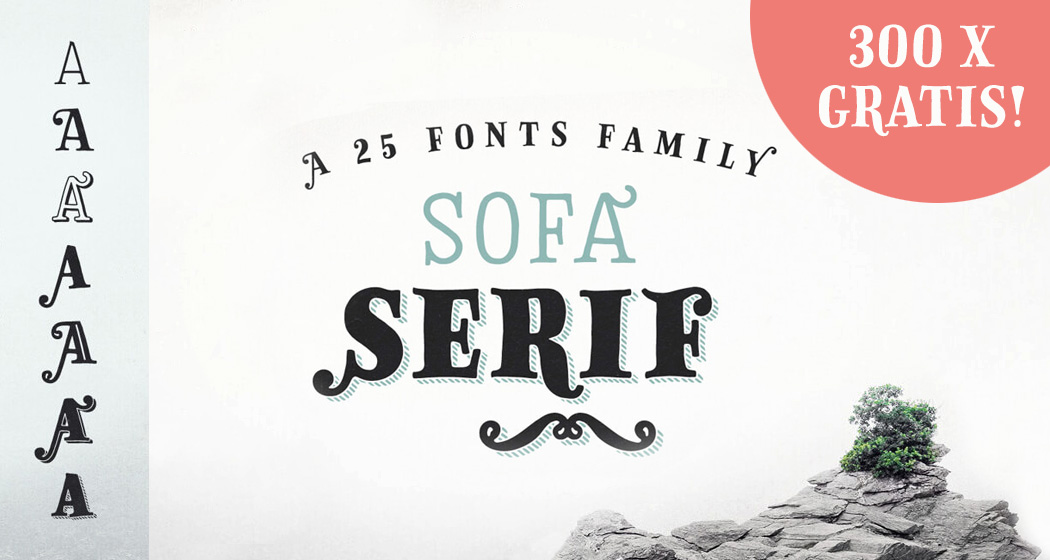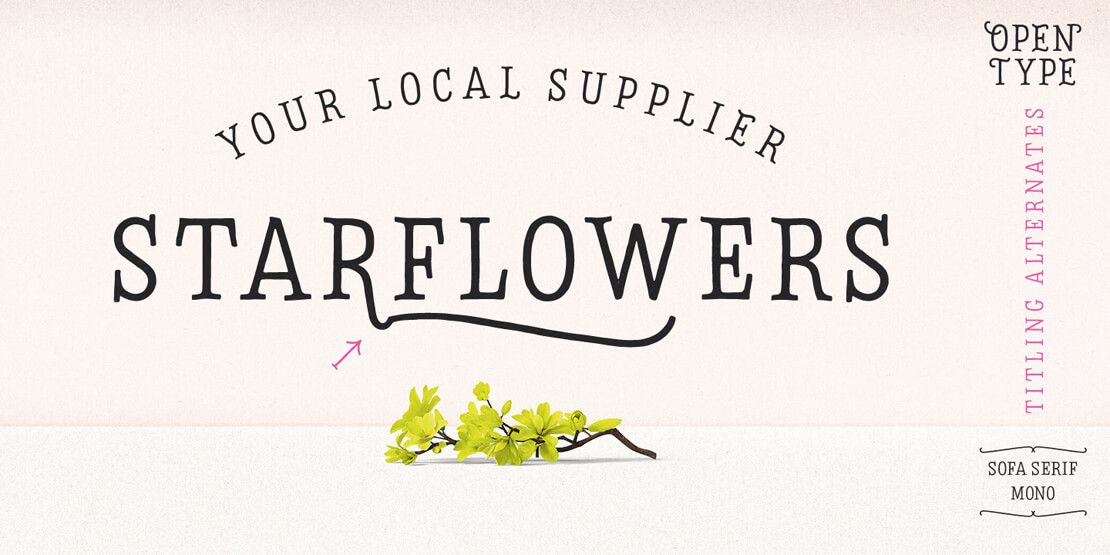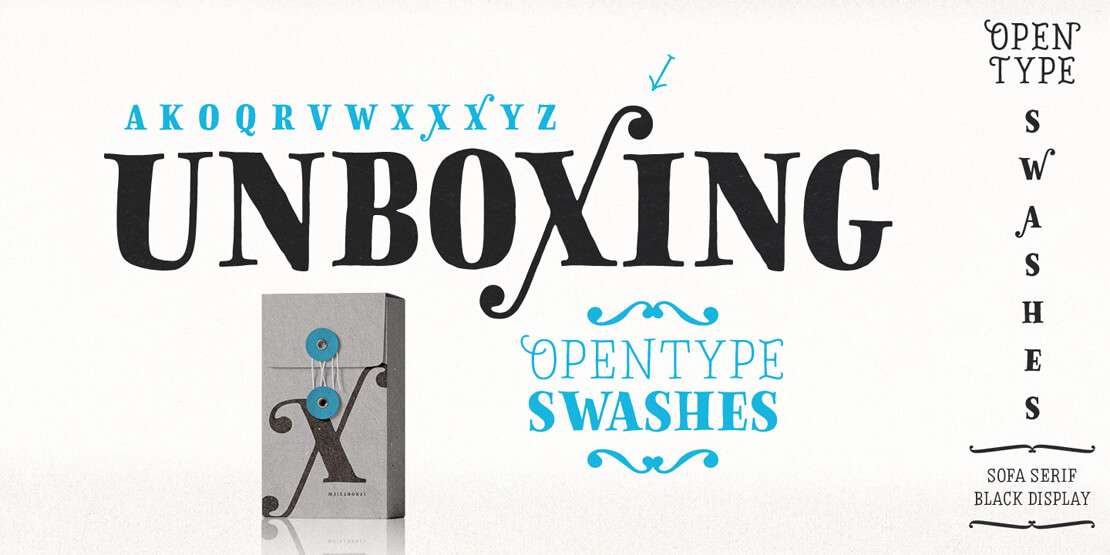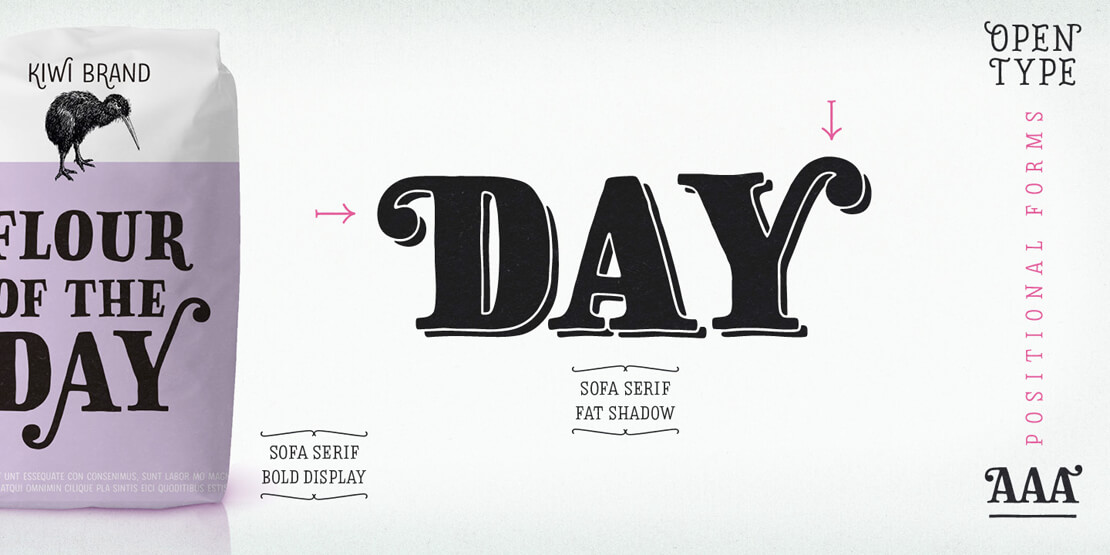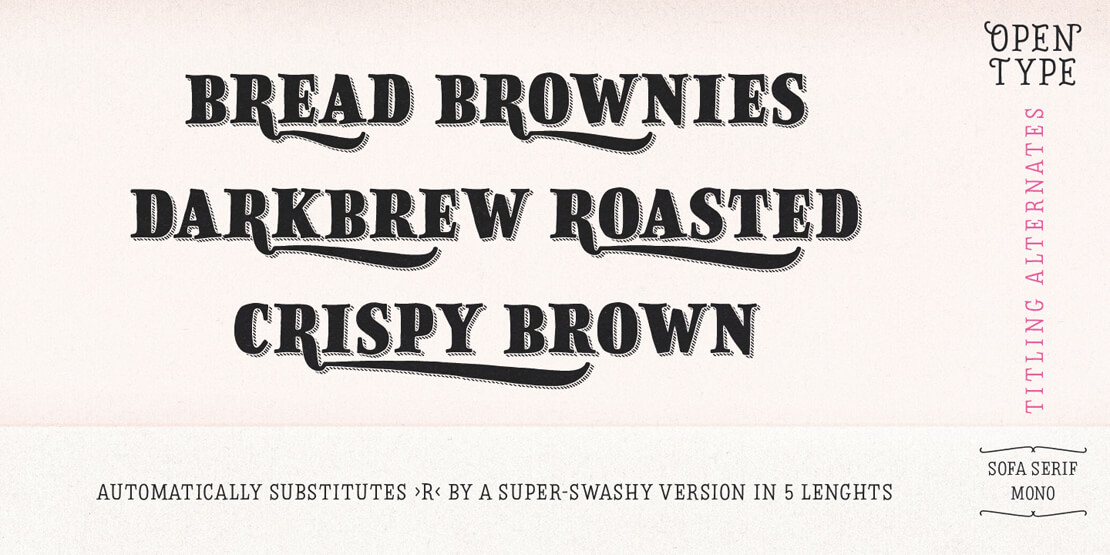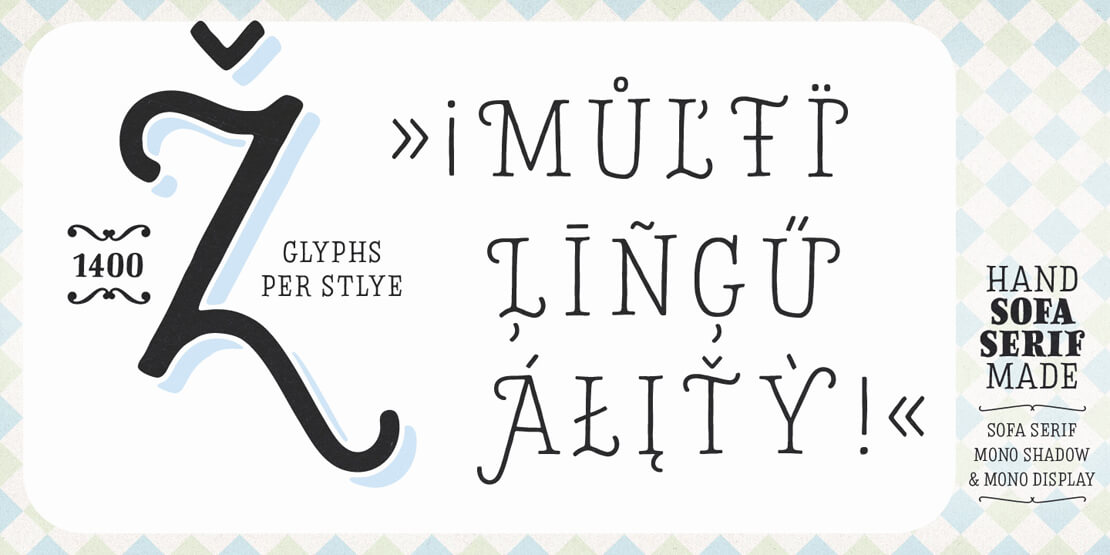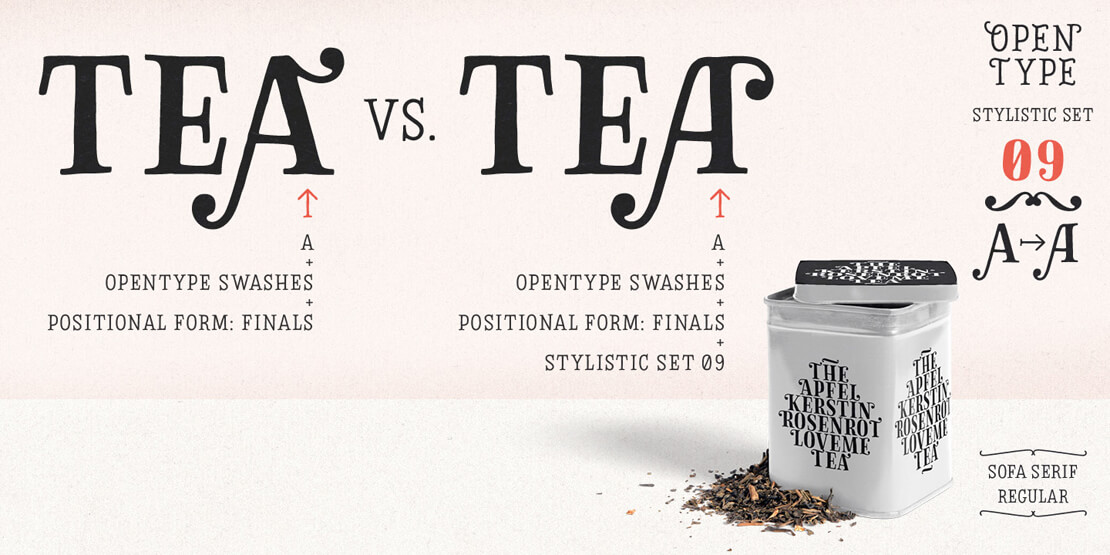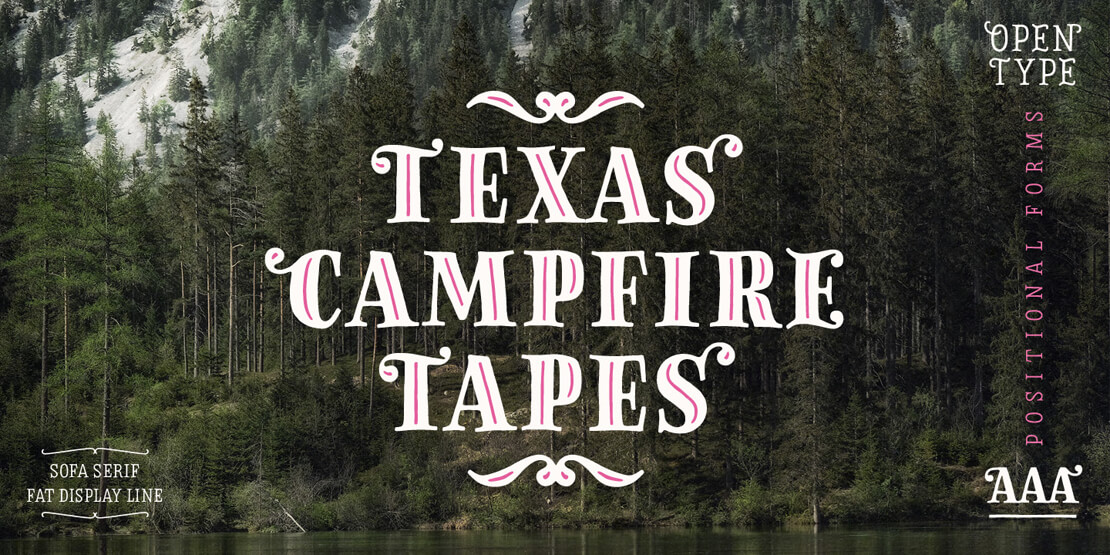
Die Sofa-Serif-Schriftfamilie besteht aus 25 handgezeichneten Schnitten. Sie bietet zudem zwei optische Größen und über 1.000 Glyphen pro Font. Für Designer in Action stellt Georg Herold Wildfellner 300 Gratis-Downloads der kompletten Schriftfamilie mit allen Fonts im Opentype-Format zur Verfügung!